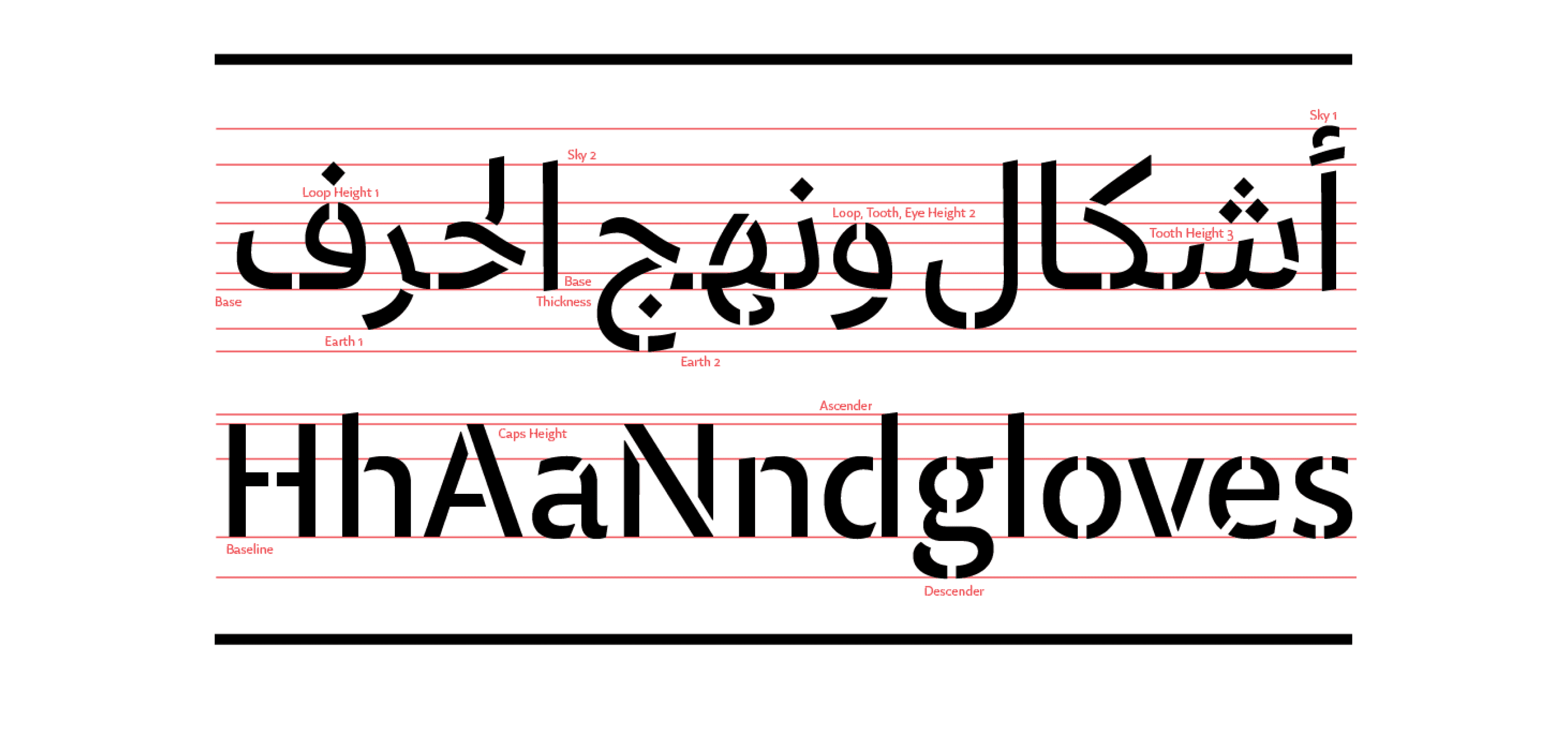
يمثل 29LT Zarid Stencil النسخة المقطّعة من عائلة Zarid Sans، ويأتي بـ 8 أوزان متنوعة من الرقيق جدًا حتى الأسود، مما يجعله مناسبًا للعناوين الجريئة والهوية البصرية الحديثة. يتميز بتوازن بين الصرامة الهندسية والطابع الحروفي العربي الأصيل، ويُستخدم في التصميمات التحريرية، والإعلانات، والتطبيقات البصرية المبتكرة.